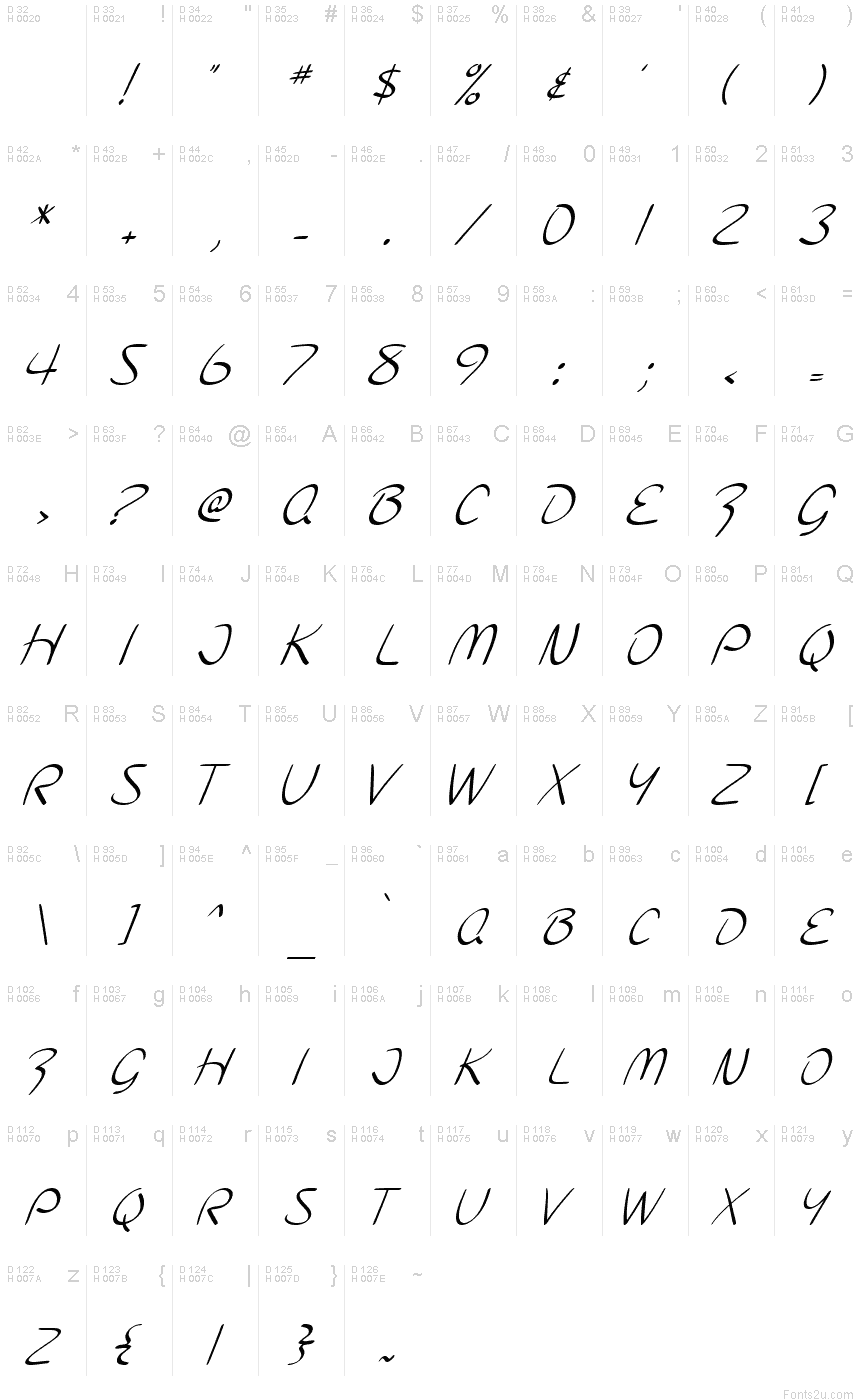
SF Burlington Script SC Italic od ShyFoundry to bezpłatny krój typu script o swobodnym charakterze, nawiązującym do ręcznie malowanych szyldów z połowy ubiegłego wieku. Wielkie litery wyróżniają się długimi, pętlowymi pociągnięciami i lekkimi łączeniami, dzięki czemu alfabet wygląda bardziej jak szybki podpis pędzlem niż formalna kaligrafia.
Krój naturalnie wpisuje się w branding butikowy, menu kawiarni, opakowania kosmetyków, nagłówki zaproszeń oraz okładki albumów czy książek – wszędzie tam, gdzie bezpłatna czcionka ma za zadanie zbudować nastrój zaledwie kilkoma znakami. Użyj go do tytułów, monogramów lub krótkich cytatów, gdy chcesz, aby te zamaszyste wielkie litery przyciągały wzrok i nadawały projektowi lekkości.
SF Burlington Script SC
ShyFoundry
Derek Vogelpohl